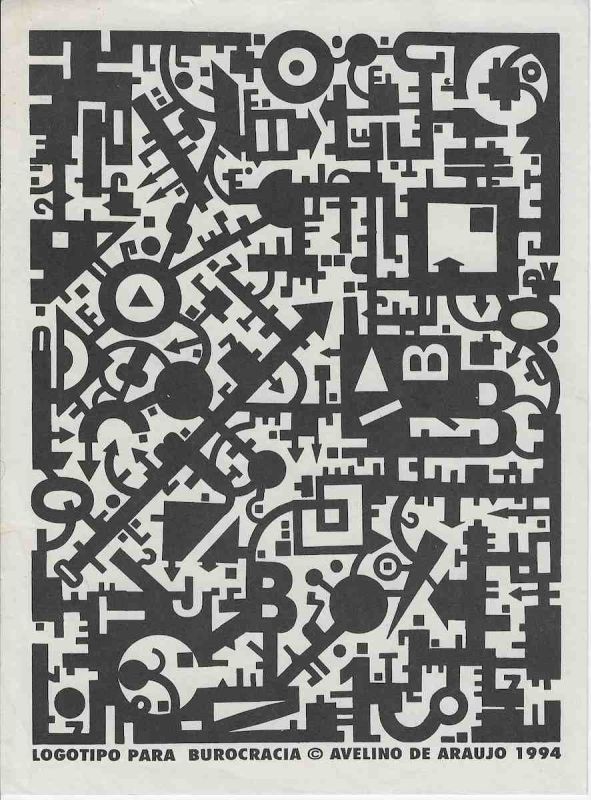
Logotipo para Burocracia é uma impressão gráfica de Avelino de Araújo realizada em 1994, vinculada à poesia visual, à poesia experimental, à arte conceitual, à tipografia e às investigações intersígnicas relacionadas ao campo do Poema Processo.
Logotipo para Burocracia é uma impressão gráfica de Avelino de Araújo realizada em 1994, vinculada à poesia visual, à poesia experimental, à arte conceitual, à tipografia e às investigações intersígnicas relacionadas ao campo do Poema Processo. A composição apresenta um grande campo retangular preenchido por letras, números, sinais de pontuação, setas, círculos, quadrados, triângulos, barras e fragmentos tipográficos de diferentes dimensões e orientações. Os elementos aparecem sobrepostos, girados, invertidos, comprimidos e encaixados, formando uma estrutura de alta densidade visual. O título propõe ironicamente a criação de um logotipo destinado à burocracia. Em vez de uma marca simples, clara e facilmente reconhecível, Avelino de Araújo constrói uma imagem saturada, labiríntica e quase impossível de decifrar. A complexidade gráfica representa visualmente os obstáculos, repetições, exigências, formulários, códigos, carimbos, procedimentos e caminhos confusos associados ao funcionamento burocrático. A palavra logotipo normalmente indica síntese, identidade e comunicação imediata, mas nesta obra ela é transformada em excesso, ruído e dificuldade. O artista converte letras e símbolos em uma massa visual que impede a leitura linear e produz a sensação de aprisionamento dentro de um sistema. As formas retangulares podem lembrar repartições, arquivos, caixas, formulários, janelas administrativas e compartimentos institucionais. As setas sugerem orientações contraditórias, deslocamentos obrigatórios e percursos sem conclusão. Os círculos, pontos e sinais gráficos funcionam como códigos, números de protocolo, registros, comandos ou marcas de validação. A repetição de caracteres e a ausência de uma hierarquia clara criam a imagem de uma linguagem administrativa que se multiplica até perder sua função comunicativa. Avelino de Araújo transforma o alfabeto em arquitetura opressiva e apresenta a burocracia como máquina de acumulação, controle, atraso e incompreensão. O campo impresso ocupa quase toda a composição e deixa poucos espaços livres, reforçando a sensação de congestionamento, excesso documental e falta de saída. O contraste entre preto e fundo claro intensifica a colisão entre figura e vazio. Logotipo para Burocracia pode ser compreendida como poema visual, sátira institucional, crítica social, diagrama do excesso e reflexão sobre o poder dos sistemas administrativos. Na parte inferior aparecem a identificação LOGOTIPO PARA BUROCRACIA, o símbolo de autoria, o nome Avelino de Araújo e o ano 1994. A obra integra a produção do artista dedicada à transformação de letras, códigos públicos, estruturas gráficas e problemas sociais em imagens poéticas e críticas. Palavras chave para indexação: Avelino de Araújo, Logotipo para Burocracia, 1994, impressão gráfica, poesia visual brasileira, poema visual, poesia experimental, arte conceitual, Poema Processo, burocracia, crítica institucional, administração pública, repartição, formulários, documentos, excesso de informação, ruído visual, labirinto gráfico, tipografia experimental, letras sobrepostas, linguagem administrativa, controle, poder institucional, comunicação visual, semiótica, intersigno, arte política, arte gráfica brasileira, múltiplo gráfico, arquivo de poesia visual, arte brasileira do século vinte.TEXT FOR THE SALSA PROGRAM IN ENGLISH: Logo for Bureaucracy is a graphic print by Avelino de Araújo produced in 1994 and associated with visual poetry, experimental poetry, conceptual art, typography and intersemiotic investigations related to the field of the Poema Processo movement. The composition presents a large rectangular field filled with letters, numbers, punctuation marks, arrows, circles, squares, triangles, bars and typographic fragments of different dimensions and orientations. The elements appear superimposed, rotated, inverted, compressed and interlocked, creating a structure of extreme visual density. The title ironically proposes the creation of a logo for bureaucracy. Instead of a simple, clear and easily recognizable mark, Avelino de Araújo constructs a saturated, labyrinthine and almost indecipherable image. Graphic complexity visually represents the obstacles, repetitions, requirements, forms, codes, stamps, procedures and confusing paths associated with bureaucratic systems. The word logo normally suggests synthesis, identity and immediate communication, but in this work it is transformed into excess, noise and difficulty. The artist converts letters and symbols into a visual mass that prevents linear reading and creates a sensation of confinement within a system. Rectangular forms may recall offices, archives, boxes, forms, administrative windows and institutional compartments. Arrows suggest contradictory instructions, compulsory movement and routes without conclusion. Circles, points and graphic signs function as codes, protocol numbers, records, commands or validation marks. Repetition of characters and the absence of clear hierarchy create the image of an administrative language that multiplies until it loses its communicative function. Avelino de Araújo transforms the alphabet into an oppressive architecture and presents bureaucracy as a machine of accumulation, control, delay and incomprehension. The printed field occupies almost the entire composition and leaves very little open space, reinforcing sensations of congestion, documentary excess and lack of escape. The contrast between black and the light background intensifies the collision between figure and emptiness. Logo for Bureaucracy may be understood as a visual poem, institutional satire, social criticism, diagram of excess and reflection on the power of administrative systems. The lower section contains the identification LOGOTIPO PARA BUROCRACIA, the authorship symbol, the name Avelino de Araújo and the year 1994. The work belongs to the artist
Impressão gráfica em tinta preta sobre papel claro, composta por um grande retângulo vertical densamente preenchido por caracteres tipográficos e formas geométricas. São visíveis letras maiúsculas, números, pontos, quadrados, círculos, triângulos, setas, barras, ângulos e módulos retangulares. Os elementos apresentam diferentes tamanhos, espessuras e orientações. Muitos aparecem girados, invertidos, fragmentados ou parcialmente encobertos por outras formas. A distribuição ocupa quase toda a área interna do retângulo e cria poucos intervalos claros. Algumas regiões apresentam grandes massas negras, enquanto outras possuem recortes brancos semelhantes a letras, corredores, janelas ou espaços vazios de uma grade. A composição produz leitura multidirecional e impede a identificação de uma sequência verbal contínua. O conjunto possui aparência de labirinto, arquivo comprimido, painel de sinalização ou sistema codificado. Na base encontra se a inscrição LOGOTIPO PARA BUROCRACIA, seguida pelo símbolo de autoria, pelo nome AVELINO DE ARAUJO e pelo ano 1994. O suporte apresenta leves ondulações, vincos, marcas de dobra, pequenas manchas, alterações de tonalidade e sinais de envelhecimento e manuseio. A peça pode ser classificada como poema visual, impressão de artista, múltiplo gráfico, colagem tipográfica, sátira burocrática e documento conceitual, sendo relevante para pesquisas sobre Avelino de Araújo, Poema Processo, poesia visual, burocracia, crítica institucional, tipografia, linguagem, semiótica e produção gráfica brasileira.OBSERVATION TEXT IN ENGLISH: Graphic print in black ink on light colored paper composed of a large vertical rectangle densely filled with typographic characters and geometric forms. Capital letters, numbers, dots, squares, circles, triangles, arrows, bars, angles and rectangular modules are visible. The elements present different sizes, thicknesses and orientations. Many appear rotated, inverted, fragmented or partially covered by other forms. Their distribution occupies almost the entire internal area of the rectangle and creates very few light intervals. Some regions contain large black masses, while others contain white cutouts resembling letters, corridors, windows or empty spaces within a grid. The composition produces multidirectional reading and prevents identification of a continuous verbal sequence. The overall structure resembles a labyrinth, compressed archive, signage panel or coded system. The lower section contains the inscription LOGOTIPO PARA BUROCRACIA, followed by the authorship symbol, the name AVELINO DE ARAUJO and the year 1994. The support presents slight undulations, creases, fold marks, small stains, changes in tone and signs of aging and handling. The piece may be classified as a visual poem, artist print, graphic multiple, typographic collage, bureaucratic satire and conceptual document, making it relevant to research on Avelino de Araújo, Poema Processo, visual poetry, bureaucracy, institutional criticism, typography, language, semiotics and Brazilian graphic production.
Logo for Bureaucracy is a graphic print by Avelino de Araújo produced in 1994 and associated with visual poetry, experimental poetry, conceptual art, typography and intersemiotic investigations related to the field of the Poema Processo movement.